Hast du jemals ein Buch einfach deshalb in die Hand genommen, weil das Cover deine Aufmerksamkeit erregt hat, nur um auf seltsam gestaltete, schwer lesbare Texte zu starren? Wir alle kennen das — schlechte Typografie kann ein großartiges Buchcover ruinieren und Leser abschrecken.
Zum Glück muss die Wahl der perfekten Schrift dir keine Kopfschmerzen bereiten. Bleib bei mir, und ich werde praktische Tipps geben, wie man klare, genrespezifische Schriftarten auswählt, sie durchdacht kombiniert und Größe und Abstand meistert, damit das Cover-Design perfekt sitzt.
Wichtige Erkenntnisse
- Verwende klare, gut lesbare Schriftarten wie Arial oder Helvetica, insbesondere in kleineren Vorschaubildern.
- Lass den Titel herausstechen, indem du große Schrift und kontrastreiche Farben verwendest, die sofort Aufmerksamkeit erregen.
- Passe den Schriftstil dem Genre des Buches an — Serifenschriften vermitteln ein vertrauenswürdiges Gefühl, fette Schriftarten verleihen Dramatik, und verspielte Schreibschriften passen zu heiteren Geschichten.
- Beschränke dich auf höchstens zwei oder drei Schriftarten, um visuelle Überladung zu vermeiden und Elemente hervorzuheben.
- Schaffe visuelles Gleichgewicht, indem du Schriftgröße und Schriftgewicht variierst – zum Beispiel große, fette Titel neben leichteren Untertiteln oder Autorennamen.
- Überprüfe Zeichen- und Zeilenabstand; der richtige Abstand verbessert Lesbarkeit und ein professionelles Erscheinungsbild.
- Überprüfe dein Cover immer in verschiedenen Größen und Formaten, einschließlich digitaler Thumbnails, um die typografische Klarheit zu bestätigen.
Wählen Sie Schriftarten, die leicht zu lesen sind
Egal, wie kreativ oder künstlerisch Sie mit Ihrem Buchcover sein möchten, wenn der Titel nicht leicht lesbar ist, verlieren Sie potenzielle Leser. Wählen Sie Schriftarten, die sauber, klar und super gut lesbar sind – selbst in der Miniaturansicht oder aus der Ferne. Sans-Serif-Schriften wie Helvetica oder Arial sind beliebte Optionen, weil sie einfach, geradlinig und sowohl in digitalen als auch in gedruckten Formaten gut aussehen. Wenn Sie sich unsicher sind, welche Schriftarten Sie wählen sollen, sehen Sie sich diesen Leitfaden an, der die besten Schriftarten für Buchumschläge abdeckt und Ihnen praxisnahe Ratschläge zur Typografie-Auswahl gibt.
Merken Sie sich: Die Lesbarkeit hat Vorrang; ausgefallene Schwünge und Schriftarten mögen verlockend sein, aber wenn die Leute nicht tatsächlich lesen können, wie Ihr Buchtitel lautet, scrollen sie einfach weiter.
Lassen Sie den Titel deutlich herausstechen
Ihr Titel ist eine der ersten Dinge, die Leser sehen, also stellen Sie sicher, dass er vom Einband hervorsticht! Ein Trick, den Designer in letzter Zeit verwenden, ist eine große Typografie, die direkt bis an die Ränder des Covers geht — oder sogar darüber hinaus. Laut einem Artikel von 99Designs ist große Typografie, die den Großteil des Raums mutig ausfüllt, momentan extrem beliebt im Jahr 2023, weil sie sofort Aufmerksamkeit erregt.
Spiele mit Kontrast – eine dunkle Schrift auf einem wirklich hellen Cover oder umgekehrt kann die Augen direkt auf deinen Titel lenken. Vermeide unruhige Hintergründe hinter deinem Text, damit dein Buchtitel nicht mit überladenen Bildern oder Mustern verschmilzt, halte ihn scharf und sichtbar, auch aus der Ferne.
Schriftarten auswählen, die dem Genre und der Stimmung des Buches entsprechen
Die Schriftarten, die du auswählst, können den Lesern eine Menge über das Genre und den Ton deiner Geschichte sagen, manchmal sogar schon, bevor sie auch nur ein einziges Wort lesen. Fette Serifenschriften liegen besonders im Trend bei historischer Fiktion, Biografien und Sachbüchern, weil sie vertrauenswürdig und autoritativ wirken — wie in einem Typografiebericht von The Book Designer hervorgehoben. In der Zwischenzeit neigen Thriller- und Horrorromane dazu, zu kühnen, großgeschriebenen Schriftarten zu greifen, um Spannung und Dramatik zu erzeugen.
Eine verspielte, informelle Schrift passt natürlich zu romantischen Komödien oder YA-Covern, während ein minimalistischer Look unglaublich gut zu literarischer Fiktion und zeitgenössischen Romanen passt. Wenn du etwas Verspieltes schreibst, wie Kinderbücher, möchtest du Schriftarten, die verspielt oder handschriftlich aussehen. Und wenn du dir noch nicht sicher bist, wie dein Buch in die Welt gelangen wird, schau dir an, wie man ein Buch ohne Agenten veröffentlicht, um die nächsten Schritte im Veröffentlichungsprozess zu gehen.
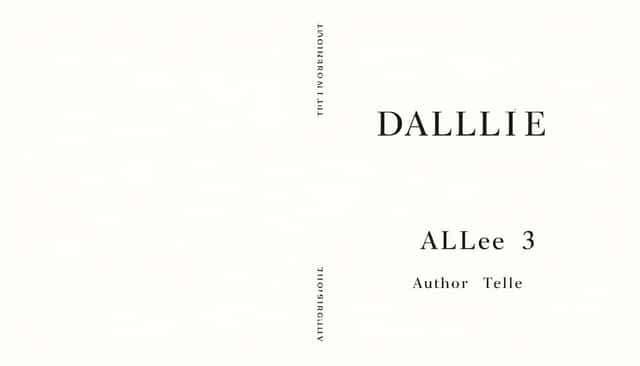
Schriftarten sorgfältig kombinieren (verwenden Sie nicht mehr als zwei oder drei)
Der ideale Bereich, Schriftarten auf einem Buchumschlag zu kombinieren, liegt in der Regel bei zwei oder drei—höchstens. Die Augen der Leser können mit zu viel visueller Komplexität nicht umgehen, ohne überwältigt zu werden, also streben Sie nach Einfachheit.
Hier ist ein schneller Trick: Wähle eine markante Schriftart für deinen Titel, etwas Auffälliges und dem Genre entsprechendes, wie eine fette Serifenschrift für historische Belletristik oder eine blockige, großgeschriebene Schriftart, wenn du eine fesselnde Horrorgeschichte-Handlung erstellst.
Dann kombiniere es mit etwas Klarem und Einfachem für deinen Autorenname oder Untertitel, wie eine serifenlose Schriftart.
Eine klassische Kombi ist eine fette Serifenschrift für den Titel, kombiniert mit etwas Neutralem – denk an Open Sans oder Roboto – für den Autorenname.
Sei vorsichtig beim Kombinieren ähnlicher Schriftarten — sie können versehentlich unpassend wirken, wenn sie zu ähnlich, aber nicht identisch sind.
Genauso wie Zuckerguss besser zu Kuchen passt als zu Eiscreme, wähle Schriftarten, die sich deutlich genug unterscheiden, damit sie sich harmonisch ergänzen und Kontrast schaffen, ohne zu kollidieren.
Verwende Schriftgröße und -gewicht, um Balance zu schaffen
Schriftgrößen und -gewichte sind dein geheimes Werkzeug, um dein Cover ausgewogen und visuell ansprechend zu halten.
Zum Beispiel ziehen große, schwere Schriftarten sofort Aufmerksamkeit auf sich – sie eignen sich perfekt, um Titel hervorzuheben – doch zu viel Fettung bei allem auf dem Cover kann aggressiv oder unübersichtlich wirken.
Balanciere dein Layout, indem du leichtere Schriftgewichte oder kleinere Größen für sekundäre Informationen wie Untertitel, Autorenname oder Slogans auswählst.
Es ist auch hilfreich, eine visuelle Hierarchie festzulegen.
Wenn der Titel einen ordentlichen Platz einnimmt, mache den Untertitel oder den Autorenname vergleichsweise kleiner und leichter.
Diese Hierarchie führt das Auge des Lesers logisch durch dein Cover – zuerst der Titel, dann Untertitel/Slogan, und schließlich der Autorenname und andere Details.
Und echte Eleganz bedeutet, vermeide den Anfängerfehler, Schriftarten zu strecken oder zu verzerren, um das Layout anzupassen — das lässt sie unprofessionell wirken.
Erhöhen Sie den Abstand zwischen Buchstaben und Zeilen für bessere Lesbarkeit
Glauben Sie es oder nicht: Subtile Anpassungen des Abstands können die Lesbarkeit und den Gesamtstil deutlich verbessern.
Der Buchstabenabstand (oder Tracking) umfasst die Abstände zwischen allen Buchstaben gleichmäßig.
Wenn Ihre Schriftart eng wirkt oder schwer zu lesen ist, versuchen Sie, das Tracking leicht zu erhöhen.
Zeilenabstand (Leading) bezieht sich auf den Abstand von einer Textzeile zur nächsten.
Eine leichte Erhöhung kann die Klarheit verbessern, insbesondere bei längeren Titeln oder Untertiteln.
Eine gute Faustregel: Bringen Sie die Zeilen nicht zu eng zusammen – sie können unscharf erscheinen – oder zu weit auseinander – sie wirken getrennt.
Sie benötigen dafür keine teure Design-Software; auch einfache Online-Tools oder Apps wie Canva können den Abstand effektiv anpassen und Ihr Buchcover professioneller wirken lassen.
Halten Sie Typografie einfach und sauber, wenn es passt
Kompliziert bedeutet nicht immer besser, besonders wenn man Buchcover erstellt, die sich an ein breites Publikum richten oder in Genres, die Minimalismus schätzen, wie literarische Belletristik oder Memoiren.
Manchmal genügt eine klare, gut lesbare Schriftart in Kombination mit ausgewogenem Abstand und gutem Kontrast.
Dieses minimalistische Flair kann für Leser, die hochwertige Inhalte statt auffälliger visueller Effekte suchen, anspruchsvoll und einladend wirken.
Durch den Einsatz geradliniger Schriftarten wie Garamond, Montserrat oder Lato kann Ihr Cover eine elegante, aber zugängliche Ausstrahlung erhalten.
Wenn Sie beispielsweise planen, ein Malbuch zu veröffentlichen, kann eine einfache Typografie Ihr Cover warm, freundlich und sofort verständlich wirken lassen.
Denken Sie daran, Einfachheit kann oft lauter sprechen als aufwändige Designs, insbesondere auf einen Blick oder in winzigen Miniaturvorschauen online.
Überprüfen Sie, wie Ihr Cover in verschiedenen Größen und Formaten aussieht (Druck und Digital)
Ihr schönes Design mag in Photoshop perfekt aussehen, es ist jedoch als Miniaturansicht auf Amazons Bestsellerliste völlig unkenntlich.
Testen Sie Ihr Buchcover immer in mehreren Größen, um sicherzustellen, dass alle Typografie lesbar bleibt und visuell ansprechend ist.
So geht's:
- Erstellen Sie eine kleine Miniaturansicht und prüfen Sie, wie gut Titel und Autorname lesbar sind.
- Halten Sie Ihre gedruckte Version in Armlänge – können Sie die Typografie problemlos lesen?
- Bitten Sie einen Freund, kurz darüber zu schauen – können Sie Genre und Stil sofort erkennen?
Die Berücksichtigung sowohl von Print- als auch digitalen Plattformen stellt sicher, dass Sie darauf vorbereitet sind, Leser zu erreichen, die Sie in Buchhandlungenregalen oder bei Online-Anbietern finden.
Dies ist besonders wichtig, wenn Sie im Selbstverlag veröffentlichen und das Buch ohne Agenten herausbringen müssen – die Lesbarkeit Ihres Covers beeinflusst den ersten Eindruck direkt.
Vermeiden Sie häufige Typografie-Fehler (überfüllter Text, schwer lesbare Stile)
Um Ihr Buchcover für alle Leser lesbar zu halten, vermeiden Sie Typografie-Fallen wie überfüllte Buchstaben, zu ausgefallene Schriftarten oder eine aggressive Großschreibung.
Designer verwenden zunehmend Schriften in Großbuchstaben, um mutige Aussagen zu machen, selbst bei weniger bekannten Autoren, laut Designhill.com.
Dieser Ansatz funktioniert, wenn er sorgfältig gestaltet ist, kann aber leicht unlesbar werden, wenn die Buchstaben zu eng beieinander stehen.
Begrenzen Sie die Wortanzahl in Ihrer Typografie auf ein überschaubares Maß, und drücken Sie lange Titel nicht auf eine Zeile.
Zerlegen Sie es in überschaubare Zeilen und nutzen Sie den Zeilenabstand effektiv.
Vermeiden Sie auffällige Script-Schriften für wesentliche Informationen wie Titel, da sie oft auf einen Blick schwer lesbar sind.
Sie möchten, dass Leser neugierig sind, nicht frustriert.
Feedback einholen und Typografie bei Bedarf anpassen
Auch erfahrene Designer bitten um Feedback, also scheuen Sie sich nicht davor.
Teilen Sie Ihr Cover mit Freunden, Autoren oder Online-Schreibgruppen und fragen Sie sie ausdrücklich nach Lesbarkeit und Genrepassung.
Fragen wie „Können Sie das aus der Ferne mühelos lesen?“ oder „Passt diese Schrift zu einer dystopischen Handlung?“ helfen dabei, konkrete Antworten zu erhalten.
Verbiegen Sie sich nicht an unterschiedlichen Meinungen — wenn mehrere dasselbe Problem nennen, handeln Sie danach.
Passen Sie Ihre Typografie an, indem Sie Größe, Abstand oder eine einfachere Schriftart wählen.
Manchmal hilft es, Meinungen von Außenstehenden zu hören, um Lücken zu erkennen, die Sie übersehen haben, wodurch Ihr Buch für Ihre idealen Leser attraktiver wird.
Häufig gestellte Fragen
Serifenenschriften wie Garamond oder Baskerville funktionieren in der Regel am besten für literarische oder historische Genres. Moderne Sans-Serif-Schriften wie Helvetica oder Montserrat passen zu Genres wie Thriller oder Sachbuch. Streben Sie stets nach Lesbarkeit und einem Stil, der zur Stimmung Ihres Genres passt.
Begrenzen Sie das Buchcover auf höchstens zwei oder drei Schriftarten. Weniger Schriftarten verwenden bewahrt visuelle Harmonie und verhindert Unordnung. Kombinieren Sie Schriftarten sorgfältig, indem Sie eine auffällige Titelschriftart mit einer einfachen, gut lesbaren Schriftart für den kleineren Text kombinieren.
Vermeiden Sie zu dekorative Schriftarten, übermäßige Texteffekte oder überfüllte Layouts, die die Lesbarkeit beeinträchtigen. Vermeiden Sie zu kleine Schriftgrößen und schlechten Zeilenabstand. Eine gute Lesbarkeit ist entscheidend, insbesondere bei Vorschaubildern oder Kleintextformaten.
Überprüfen Sie das Cover-Design auf Bildschirmen unterschiedlicher Größe und in gedruckten Formaten. Passen Sie Abstände, Schriftgewicht und Größe entsprechend an. Feedback von Lesern ist hilfreich, um Lesbarkeitsprobleme auf verschiedenen Plattformen zu identifizieren.